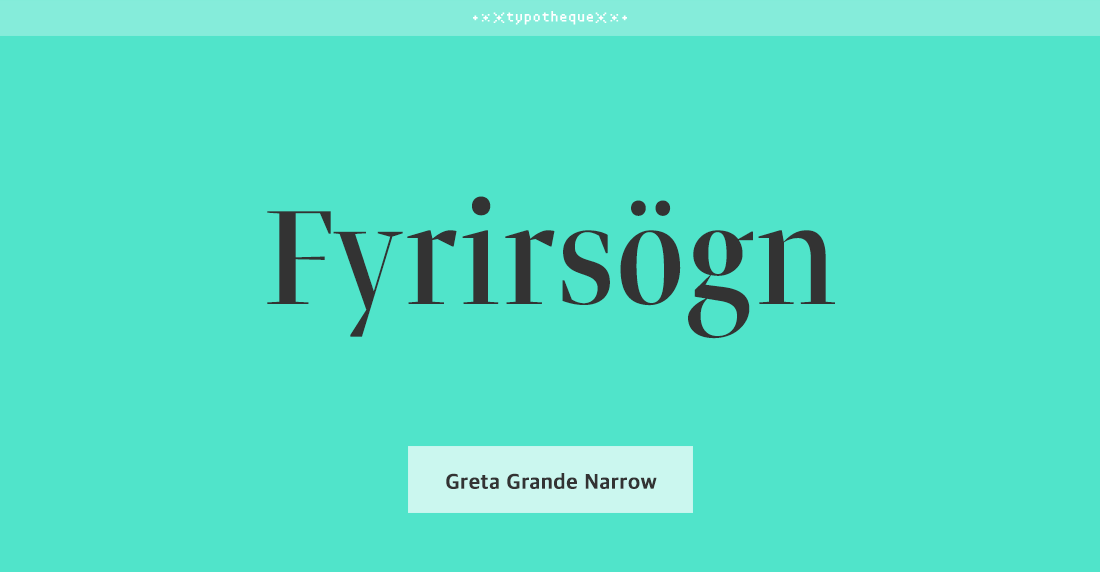
- Greta Grande Narrow Std는 큰 헤드 라인을 대상으로 하며 두껍고 좁은 간격 및 속공간 사이의 대비를 고려하여 설계되었다.
헤드라인에 가장 적합하고 다른 Greta 폰트와 함께 쓴다면 더할 나위 없이 완벽한 디자인을 완성할 수 있을 것이다.
Narrow는 베이직한 Grande 폰트보다 더 좁은 공간에서 유용하게 사용이 가능하다.
폰트 정보 구분 명조 디자인디렉팅 Peter Biľak, Nikola Djurek 출시년도 2008